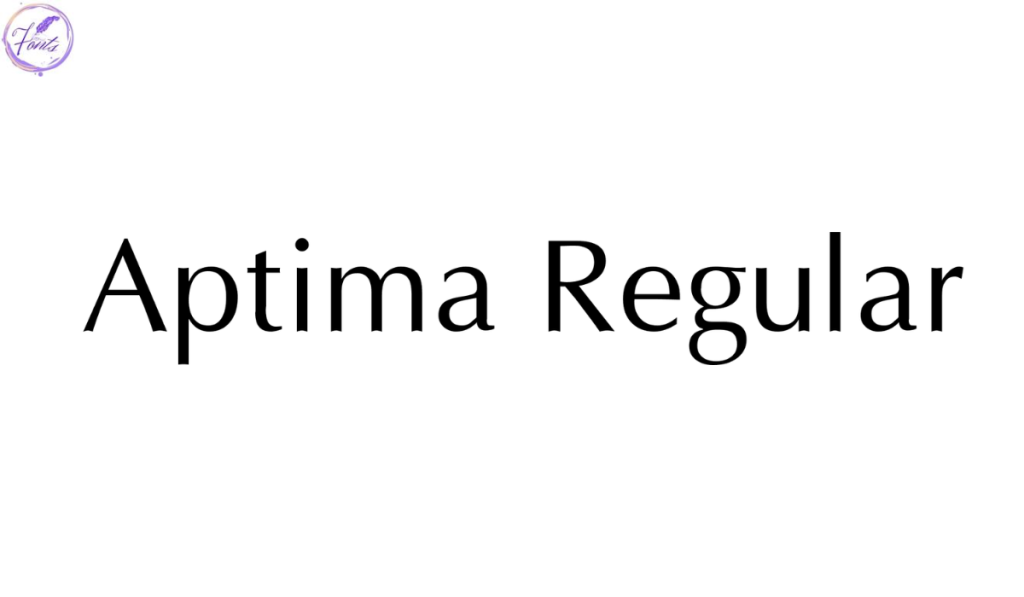
Aptima font việt hóa
Tác giả: Microsoft
Ngày phát hành: 2003
Ngôn ngữ: Tiếng Việt, nhiều ngôn ngữ khác
Bộ Font: Aptima
Phân loại: Cá tính, độc đáo
Kiểu chữ: Sans-serif (không chân)
Độ dày: Regular, Bold, Italic, Bold Italic
Aptima font là một bộ font hiện đại, mang phong cách đơn giản nhưng không kém phần tinh tế. Được tạo ra bởi nhà thiết kế Microsoft vào năm 2003, font này nhanh chóng trở thành lựa chọn ưa thích của nhiều nhà thiết kế đồ họa. Aptima font được thiết kế với các đường nét rõ ràng, sạch sẽ, dễ đọc và phù hợp với nhiều loại dự án khác nhau như in ấn, thiết kế web, và các ứng dụng kỹ thuật số. Phiên bản Việt hóa của aptima font giúp người dùng Việt Nam dễ dàng sử dụng trong các văn bản tiếng Việt, tạo nên sự đồng nhất và chuyên nghiệp cho mọi thiết kế.
Đánh giá aptima font
Aptima font được đánh giá cao bởi cộng đồng thiết kế nhờ vào tính thẩm mỹ và sự linh hoạt của nó. Những đường nét mượt mà, cân đối của font này không chỉ tạo cảm giác dễ chịu khi nhìn mà còn giúp truyền tải thông điệp một cách rõ ràng và hiệu quả. Các nhà thiết kế đánh giá cao aptima font vì khả năng thích ứng với nhiều loại hình thiết kế khác nhau, từ các dự án quảng cáo đến các ấn phẩm truyền thông. Phiên bản Việt hóa của aptima font cũng được đánh giá cao vì giữ nguyên được phong cách gốc, đồng thời bổ sung đầy đủ các ký tự tiếng Việt, đáp ứng mọi nhu cầu sử dụng của người dùng.